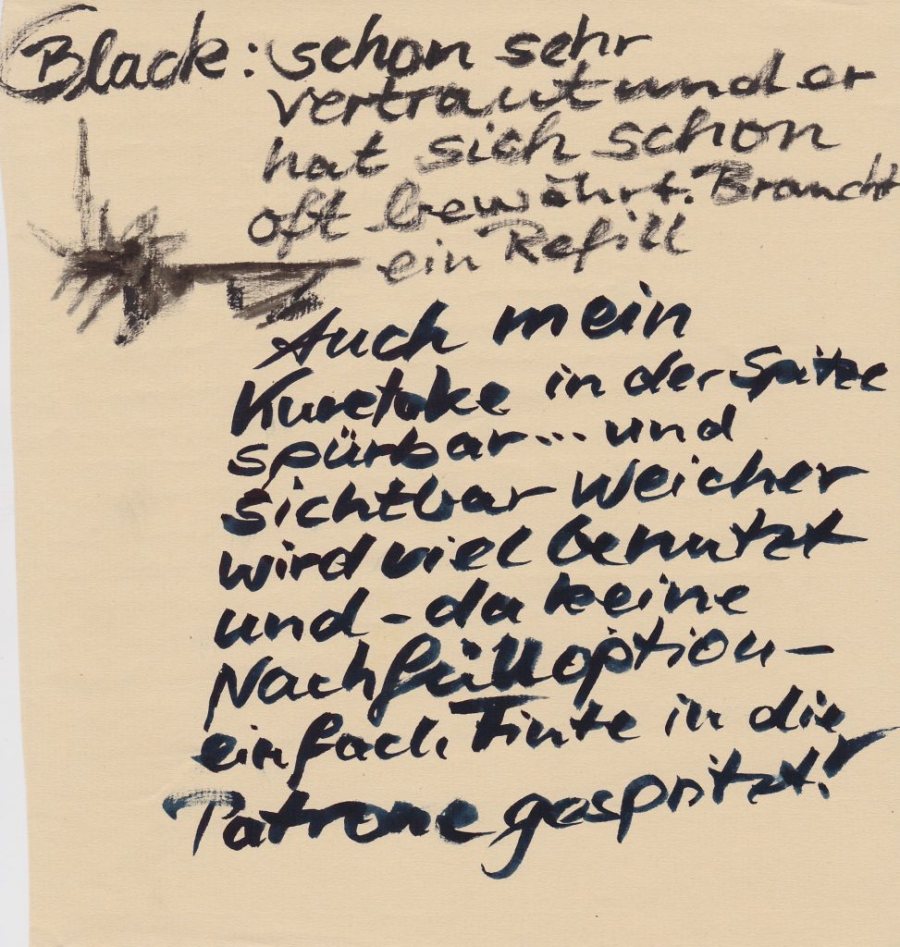
Pentel Pocket Brush im Praxistest
Vielseitig, praktisch und jetzt in neuen Farben
Hoch erfreut durfte ich die neuen Farben des Pentel Pocket Brush testen! Den schwarzen nutze ich schon seit Langem und schätze ihn für seine Vielseitigkeit und die präzisen Linien. Kennengelernt habe ich ihn beim Urban Sketching – seitdem begleitet er mich ständig in meinem kreativen Alltag.
Ein Stift für jede Gelegenheit
Der Pocket Brush bietet mit seiner einzigartigen Pinselspitze so viele Möglichkeiten, dass man kaum aufhören kann, neue Effekte zu entdecken. Besonders unterwegs ist er unschlagbar: Ob in der Stadt, in der Natur oder sogar am Strand im Sand – er macht immer eine gute Figur.
Mich fasziniert vor allem die enorme Strichvielfalt. Mit wenig Druck entstehen feine Linien, mit mehr Druck kräftige, manchmal auch ausgefranste Striche. Damit ist er Allrounder für filigrane Details und expressive Akzente zugleich.
Vergleich und Experimente
Ich habe auch den Pocket Brush von Kuretake, den ich auf der Paperworld entdeckt habe. Im Vergleich ist dessen Spitze weicher, die Linien wirken fließender. Mir persönlich gefällt der grobe Strich des Pentel besser, er hat mehr Charakter.
Spannend ist auch, was passiert, wenn die Tinte fast leer ist: Der Stift bietet immer noch Gestaltungsmöglichkeiten. Mit einem Wassertankpinsel lassen sich die Striche anlösen, auf feuchtem Papier entstehen faszinierende Farbverläufe. Für unterwegs reicht mir meist schon Schwarz und Grau, aber auch der warme Erdton und das dunkle Braun aus dem Testset haben ihren Reiz.
Kreativ leicht unterwegs
In meinem kleinen Federmäppchen habe ich vier Brush Pens, einen Bleistift und ein Leporello – das wiegt weniger als 100 Gramm und reicht für lange Fahrrad- oder Wandertouren. Auch verschiedene Papiere habe ich ausprobiert: Auf rauem Büttenpapier wirken die Striche ganz anders als auf einfachem Druckerpapier. Selbst auf Skizzenpapier bleibt die Rückseite sauber, was unterwegs ein echter Vorteil ist.
Mein Fazit
Ich habe den schwarzen Pocket Brush immer schon geliebt und jetzt durfte ich die verschiedenen Farben testen. Sie eröffnen noch mehr kreative Möglichkeiten, machen das Lettern abwechslungsreicher und das Skizzieren lebendiger. Ob schnelle Skizzen, detaillierte Letterings oder expressive Linien: Der Pocket Brush überzeugt durch Vielseitigkeit, Qualität und praktische Handhabung. Für alle, die unterwegs kreativ sind, ist er eine echte Empfehlung!
Besonders in Kombination der Farben mit den bewährten Eigenschaften des schwarzen Pinselstifts lassen sich beeindruckende Effekte erzielen. Ob für schnelle Skizzen, detaillierte Lettern oder expressive Linien – die Farben bereichern mein Arsenal an Werkzeugen ungemein. Insgesamt bin ich begeistert von der Vielseitigkeit, der Qualität und der praktischen Handhabung dieser Pinsel. Für alle, die gerne unterwegs kreativ sind, sind sie eine echte Empfehlung!